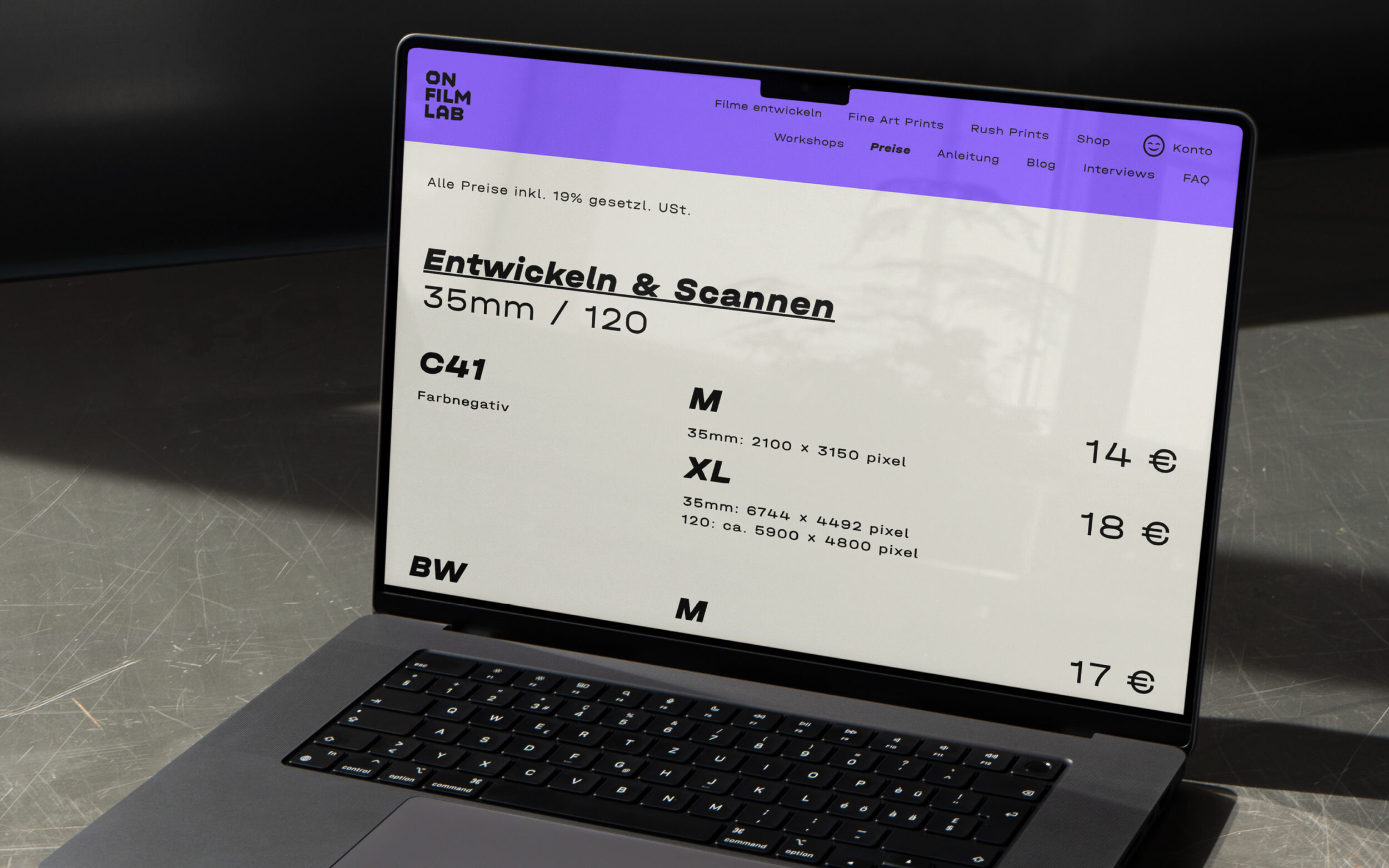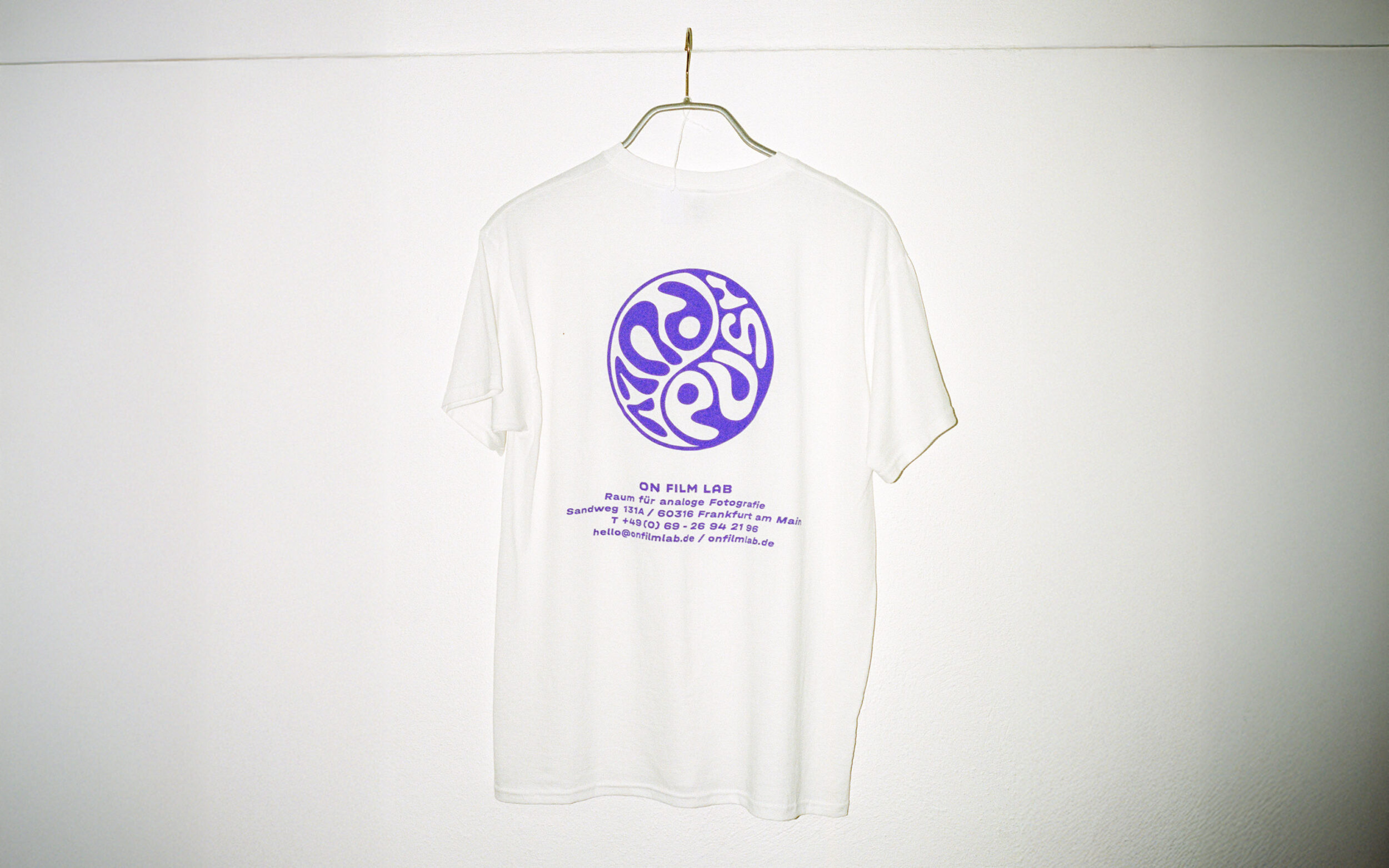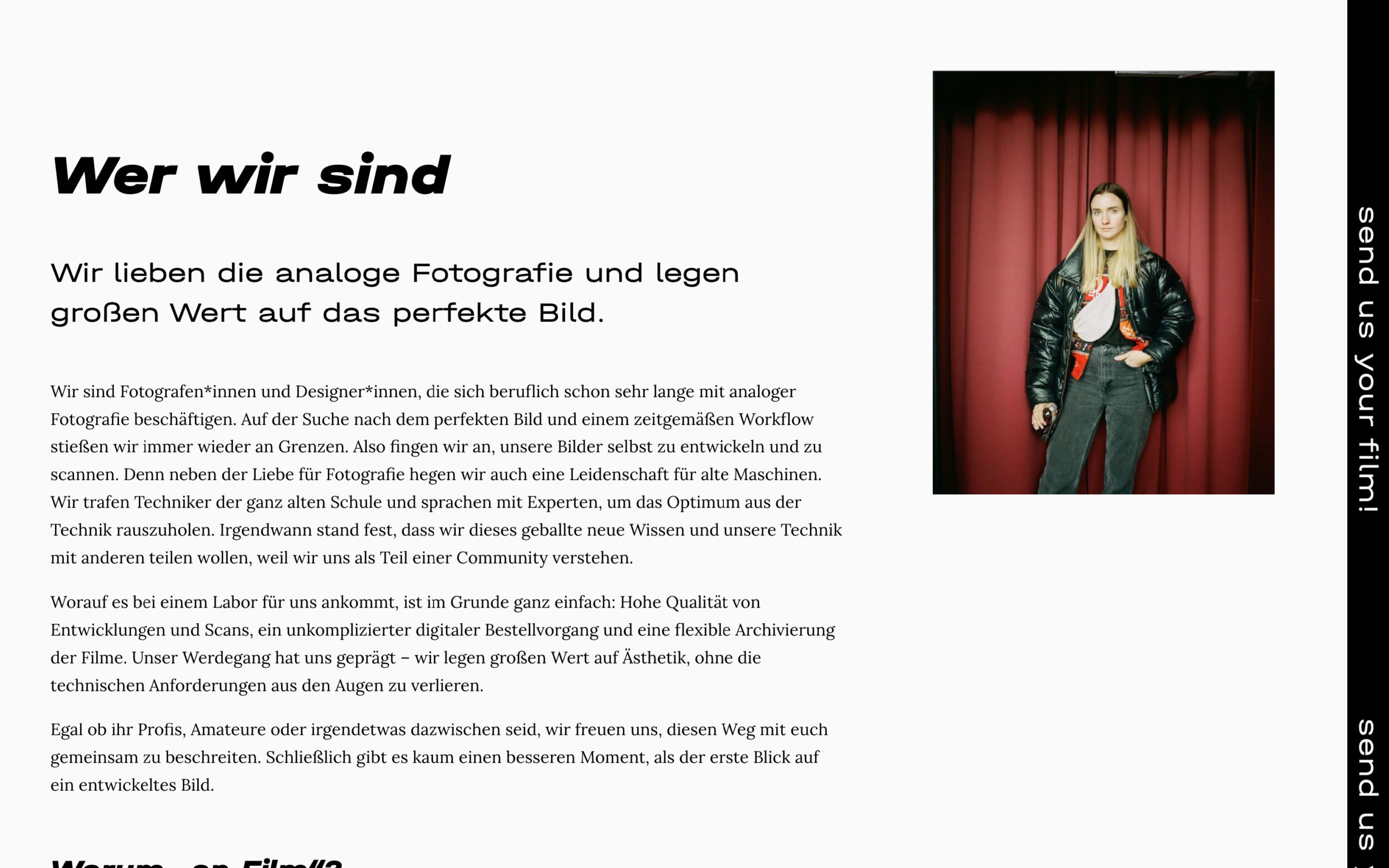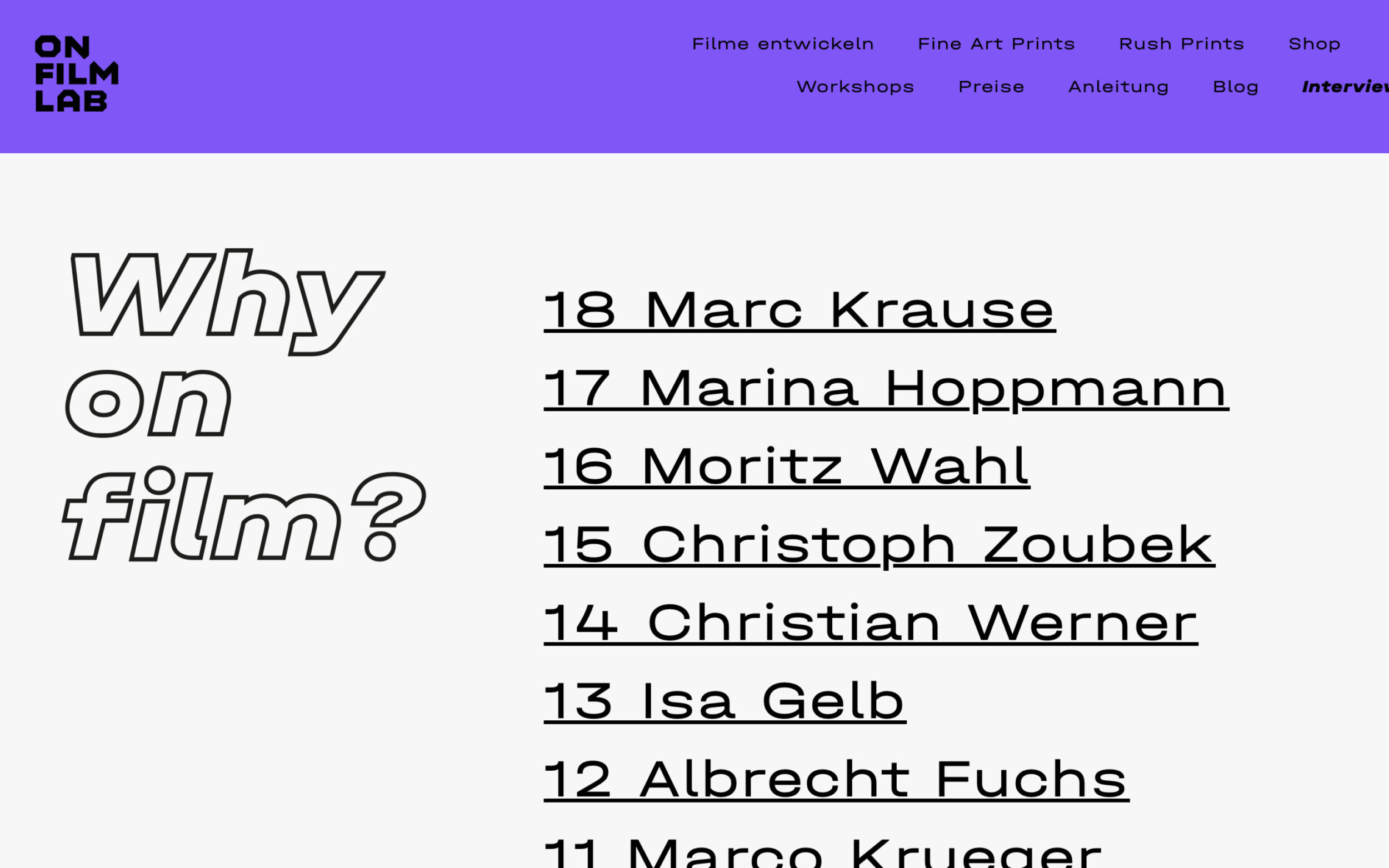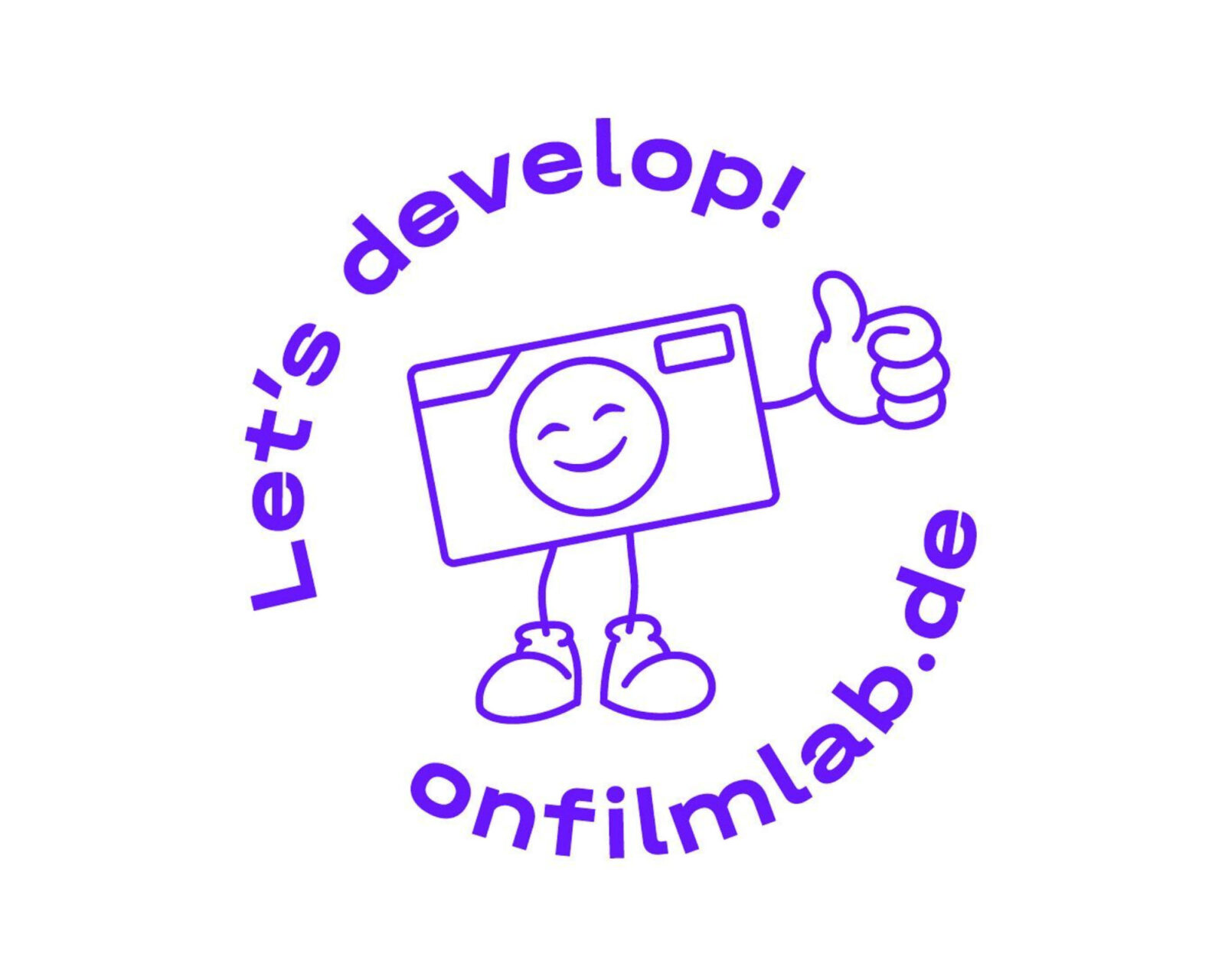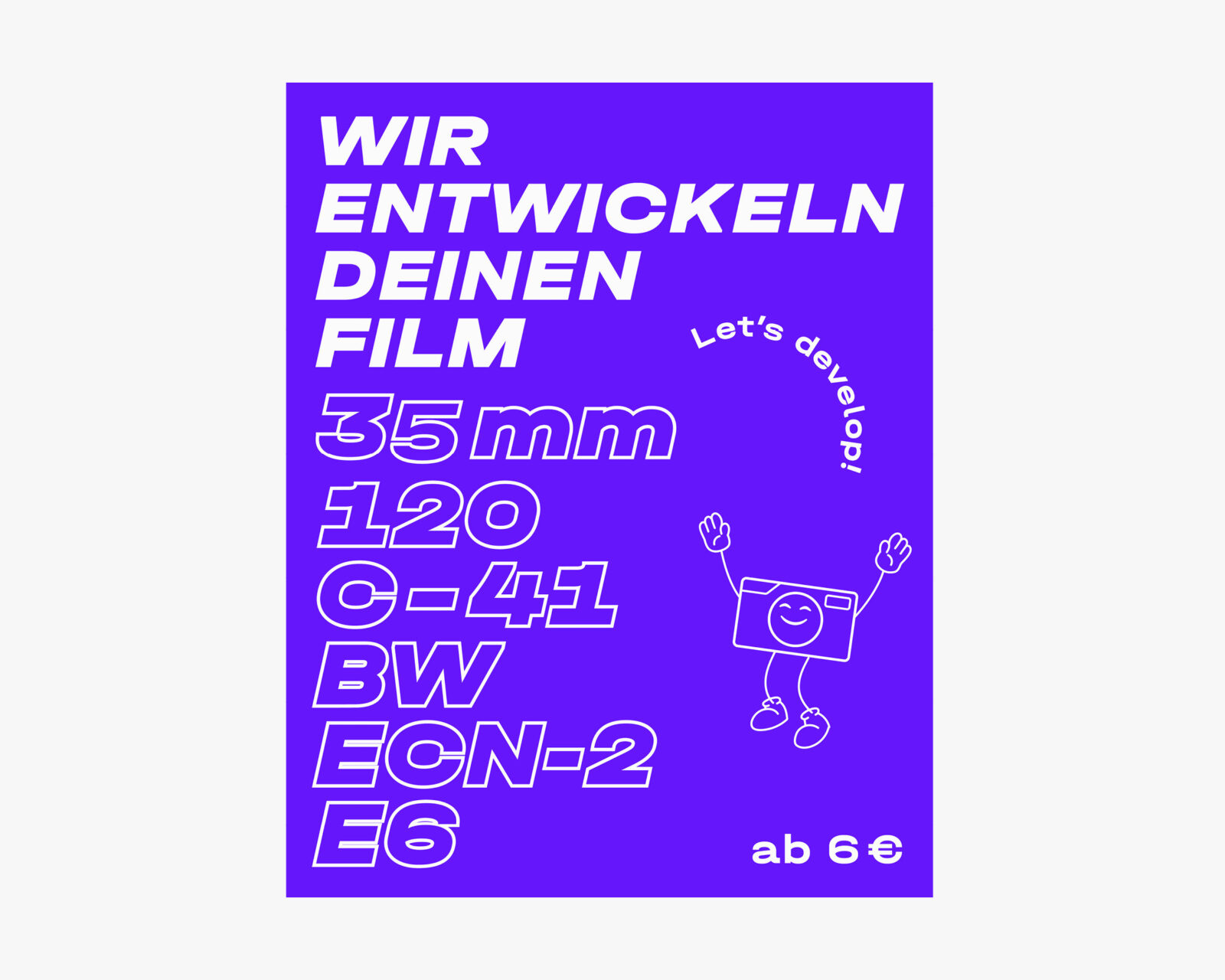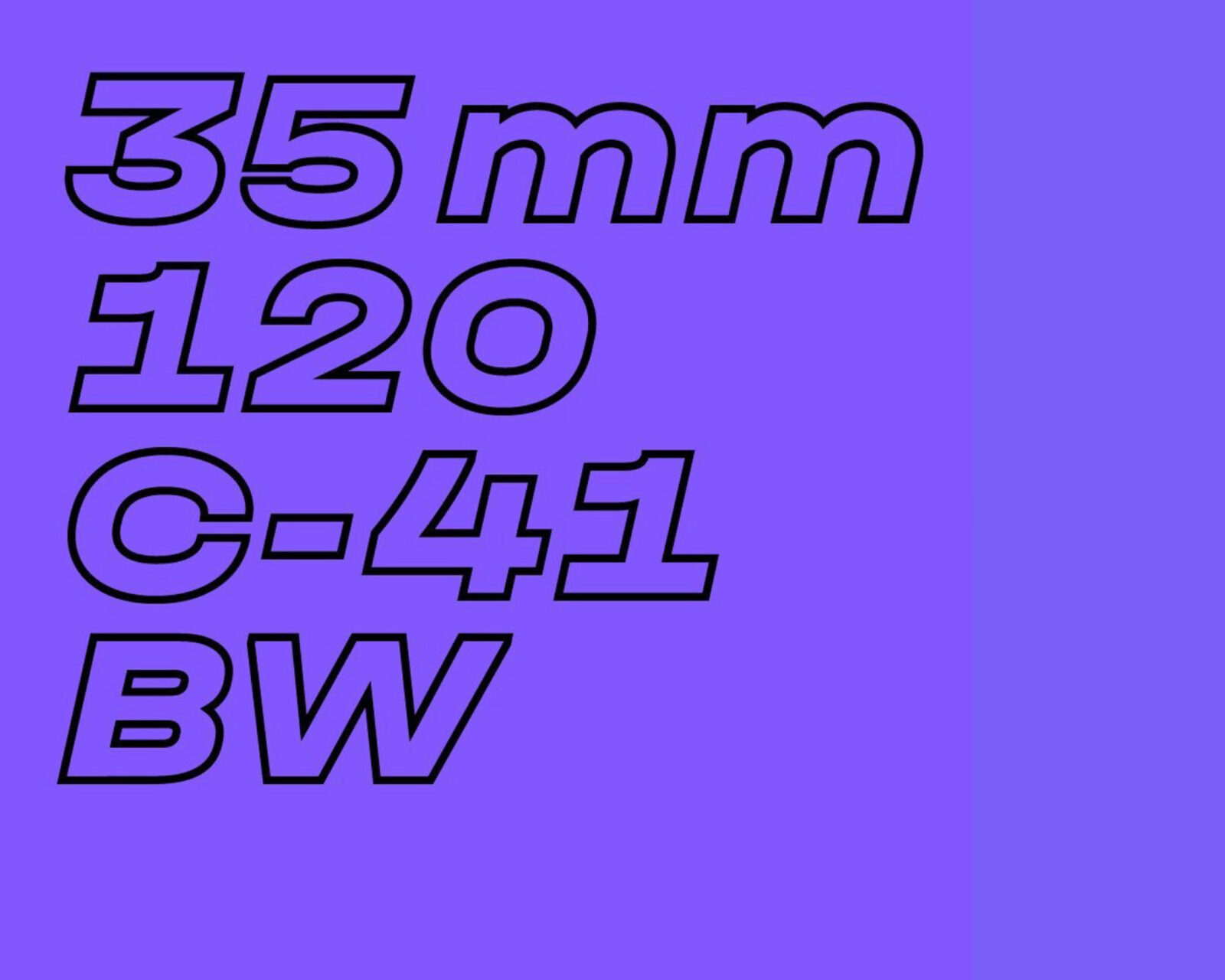
Für das Corporate Design des Fotolabors „On Film Lab” verbindet Halvar Breitschrift die industrielle Tradition der analogen Fotografie mit zeitgenössischer Dynamik.
Das ON FILM LAB ist ein Fotolabor in Frankfurt am Main, das sich der Liebe und dem Entwickeln von analogen Fotografien verschrieben hat. Es richtet sich an Profis und Amateure und bietet alles rund um analoge Filmentwicklung an. Für das Branding spielt die Schriftart Halvar eine zentrale Rolle. Mit Ausnahme von Lesetexten und dem Logo kommt sie durchgängig zum Einsatz – und das aus gutem Grund.
Halvar spiegelt mit ihrem industriellen Charme den technischen Charakter des Fotolabors wieder. Als Breitschrift wirkt sie zugleich frisch und jung, passend zum Zielgruppe. Die Superslanted verleiht dem Design zusätzlich eine dynamische, moderne Note.